炎炎夏日,大暑节气即将降临!在这个盛夏时节,让我们一起迎接大暑,共享夏日的热情和活力!我们特别为大家准备了一场别开生面的字体展示,让文字也尽情绽放光彩。
Aa饱和脂肪酸以膨胀的几何笔画结合横细竖粗对比鲜明的宋体笔形结构形成一款膨胀可爱的创意宋体。
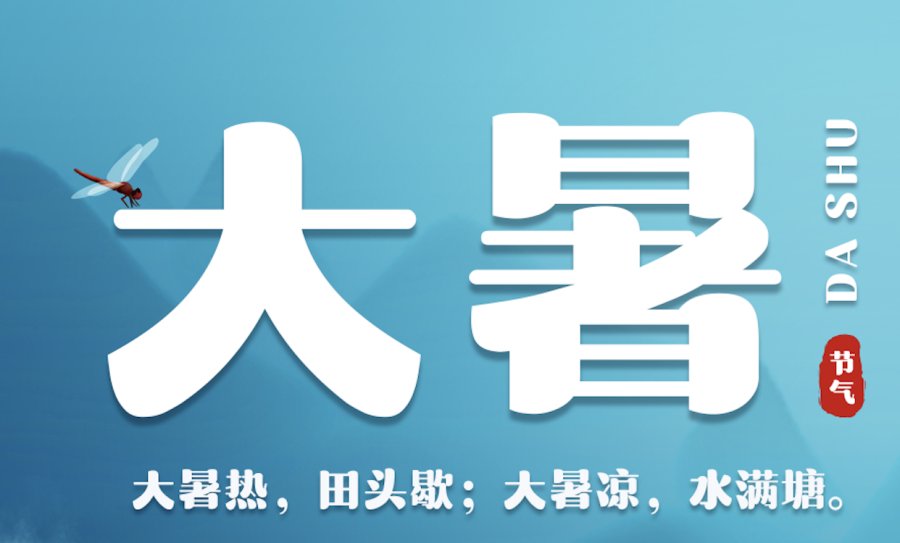
上首东坡体,字体笔画横细竖粗,整体字型宽扁方正,沉稳肃穆,粗壮醒目。字体特点鲜明,艺术感十足,适用于搭配标志、广告标语、商业广告、海报字体等高端属性。
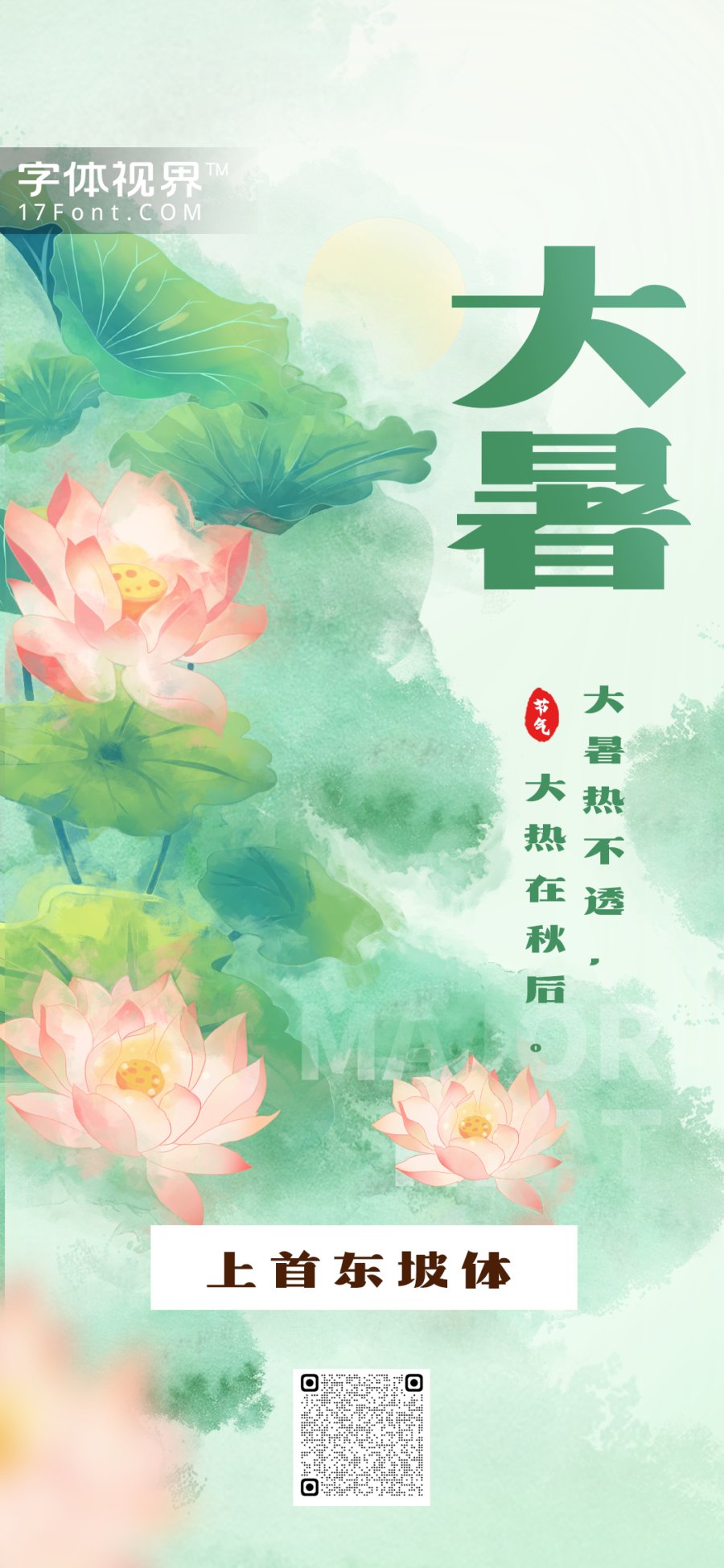
Aa鲸潮体吸收了日本书法特征的手书字体,笔画点染任性而不任意。
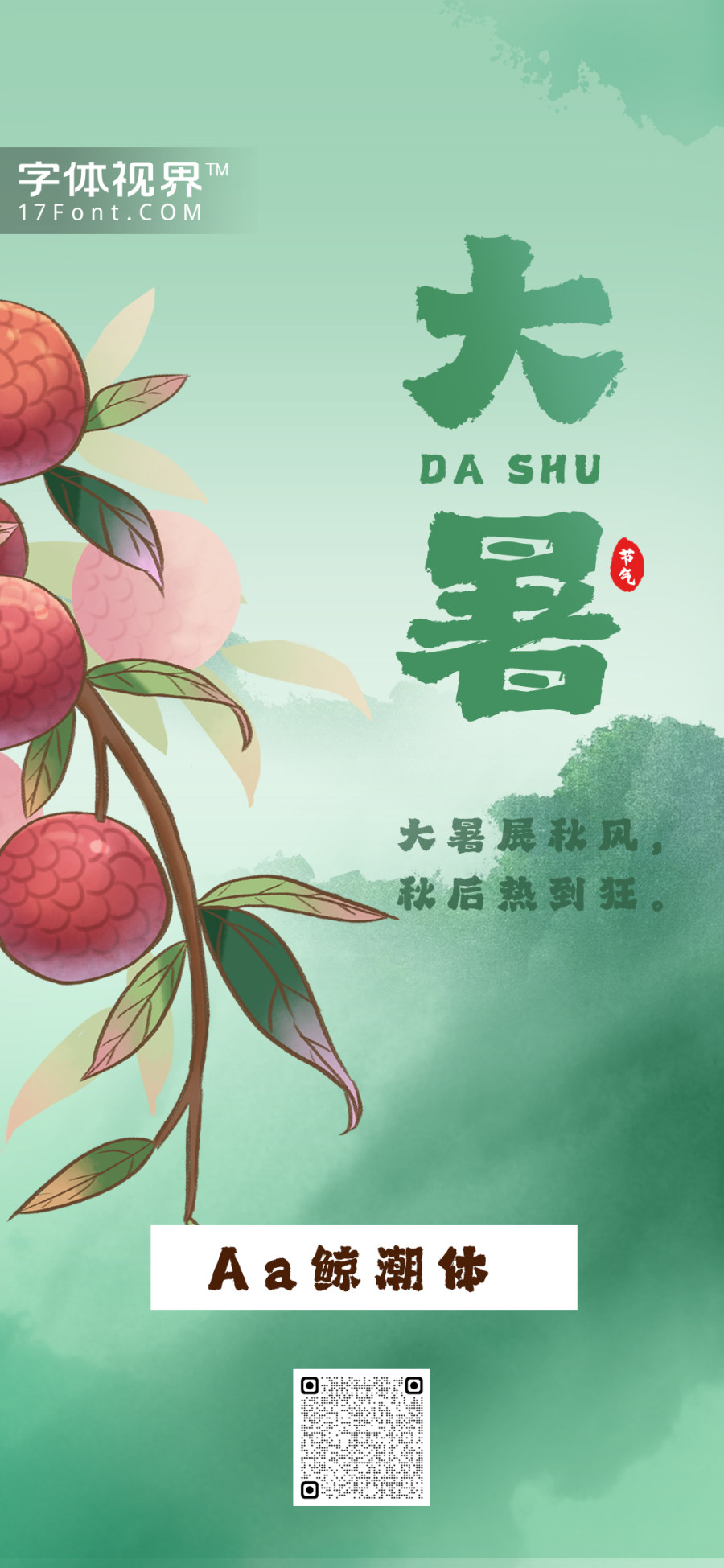
字语文新宋字体笔画圆润,减少了宋体具有相对锋芒修饰感,韵律节奏恰如其分,字形流畅,中宫放松,横竖笔画粗细比例合理。